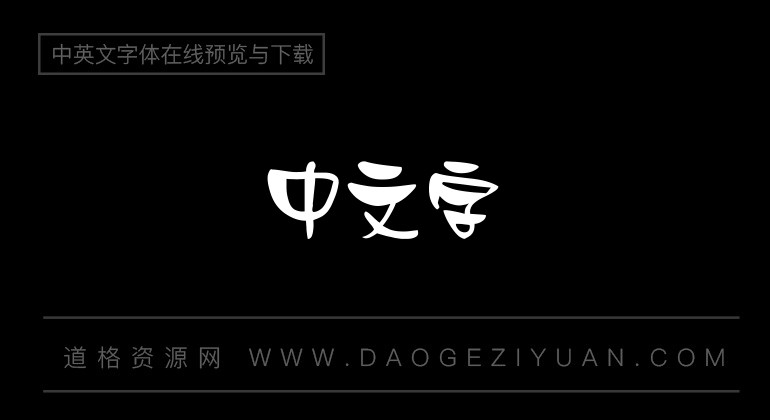
金梅浪漫原体国际码
? 金梅浪漫原体国际码字体是一款简约时尚的英文字体,字体风格自然优雅,曲线流畅,给人一种温暖舒适的感觉。字体以细节为重点,细节上细腻,线条精致,让字体更加精致,给人一种温暖的感觉。字体表面既有温柔的曲线,又有精致的线条,给人一种舒适的感觉。
金梅浪漫原体国际码是一款非常不错的手写艺术字体,具有很好的视觉感,适合于文化类的宣传设计、商业类品牌的广告和产品包装设计以及个性化文字排版等较多场景。